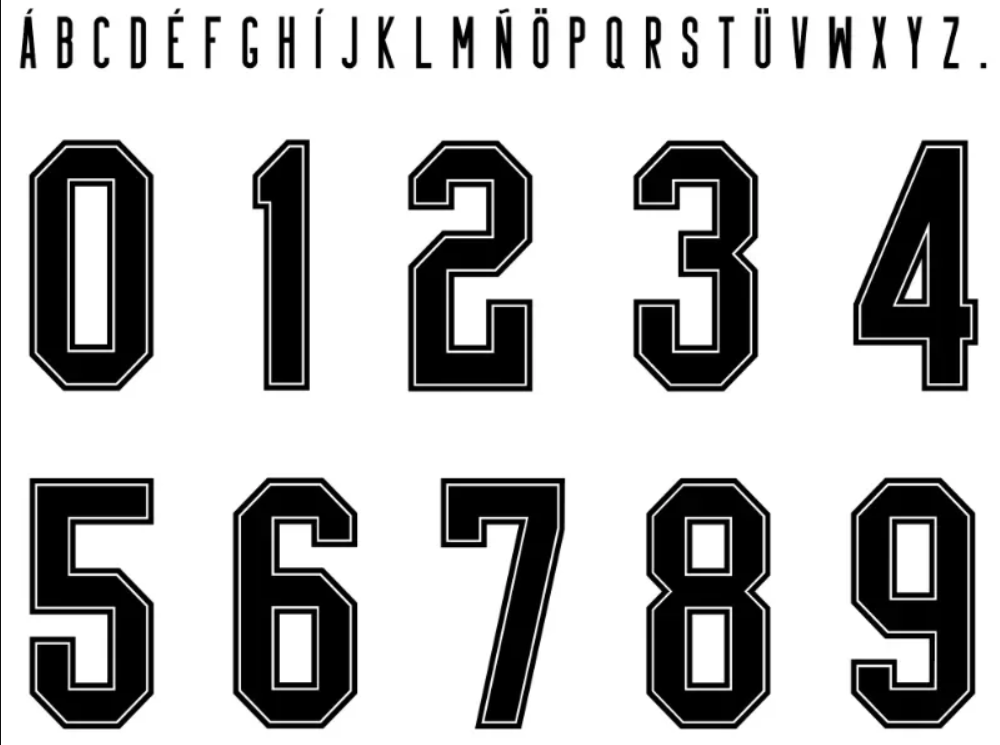
Se você procura a tipografia exata para personalizar mantos sagrados, chegou ao lugar certo. A temporada de 2018 foi marcante para o Corinthians, trazendo uniformes produzidos pela Nike que misturavam tradição e homenagens históricas (como a inesquecível “Democracia Corinthiana” e a terceira camisa em tributo a Ayrton Senna).
Para garantir que suas artes, mockups ou personalizações de camisas fiquem com o visual oficial de jogo, disponibilizamos o arquivo da fonte utilizada pelos jogadores naquela temporada. É a peça que faltava para deixar seu projeto com a cara do Timão.
Estilo Visual e Identidade
A tipografia do Corinthians em 2018 segue o padrão de design industrial e moderno proposto pela Nike para seus principais clubes globais naquele ano, mas com toques exclusivos para o Alvinegro.
A fonte apresenta traços sólidos e angulares, garantindo alta legibilidade tanto no estádio quanto na TV. Diferente de fontes retrô, ela possui um corte futurista nos números e letras, transmitindo velocidade e agressividade. É a escolha perfeita para quem deseja recriar as camisas 1 (branca) e 2 (listrada) daquele ano, mantendo a fidelidade estética que o torcedor exige.